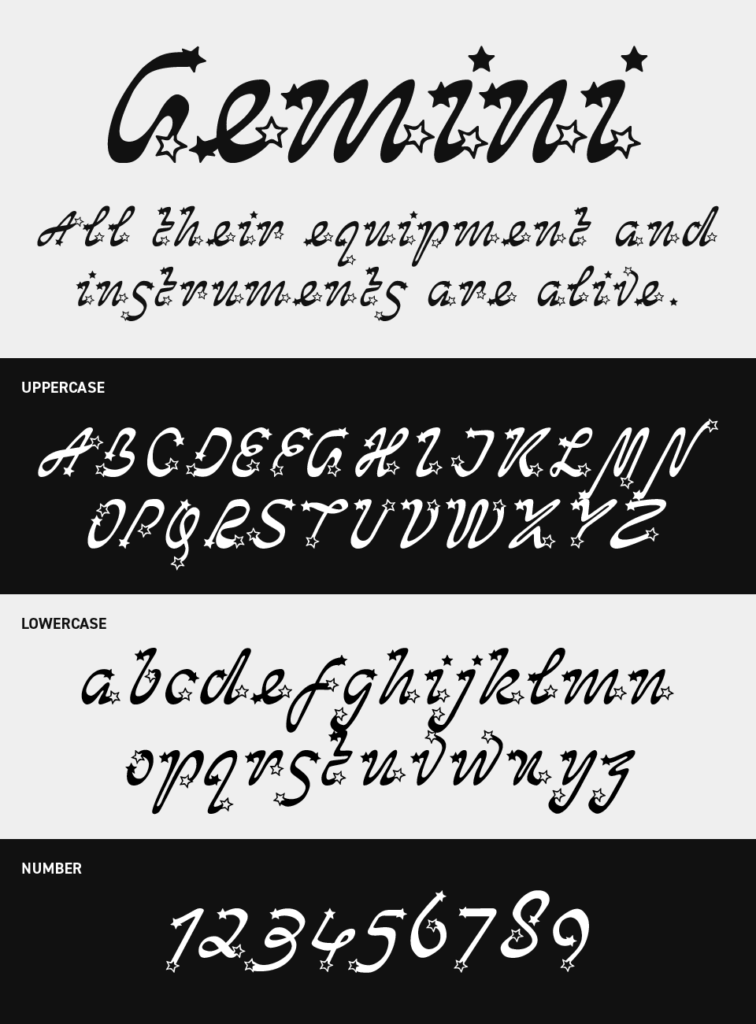
Stardom Font
Geminiフォントは、流れるような筆記体に小さな星モチーフが散りばめられたロマンチックなデザインが特徴のデザインフォントです。
大きく弧を描く頭文字や、文字の終わりにきらめく星の装飾がアクセントになり、まるで夜空に文字を書いたような幻想的な雰囲気をまとっています。
装飾性が高いため、タイトルやロゴ、バースデーカードやコスメ系ビジュアルなど、世界観を大切にしたい場面にぴったりなフォントです。可愛らしさと華やかさが同居しており、特別感を演出したいデザインにおすすめのフォントです。